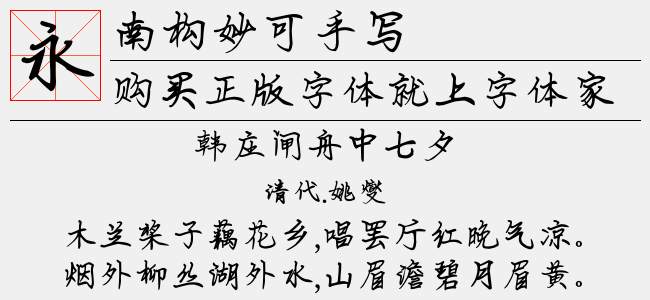
南构妙可手写
字体作者:刘禹彤
字体名称:南构妙可手写
字体字数:26个英文大小写字母及和阿拉伯数字和6763个汉字
字体家族:南构手写体系列
书体类型:书法类
南构妙可手写
南构妙可手写是一款非常不错的手写艺术字体,由南构字库出品,端正大气,书写的十分有韵律,字库完整,适应于报纸和杂志和书籍中常用字体, 海报、个性促进品牌标志设计、字体设计、等环境使用,欢迎喜欢的朋友前来字体家下载使用。
字体介绍:
南构妙可手写是自创的一款特色字体,字体娟秀却不失风骨。柔美中夹杂着硬朗和个性。通过笔画凸显的曲折变化,字里行间既流动着簪花小楷的灵秀之气,亦有不折不挠的个性笔体特征。南构妙可手写字体既有古代字体钟灵毓秀的美感,亦有近现代字体的大气且不拘一格的铮铮傲骨之风貌。